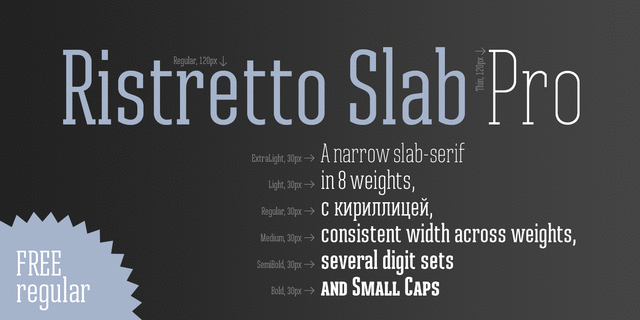
Ristretto Slab Pro – это брусковый компаньон шрифта Ristretto Pro. Это сверхузкий акцидентный шрифт с асимметричными брусковыми засечками, доступный в 8 насыщенностях. Гарнитура поддерживает множество языков, 6 наборов цифр и капитель.
Шрифт Ristretto Slab Pro разработал и выпустил Андрей Константинов в студии Mint Type в 2013 году.
Ассоциации c начертанием Ristretto Slab Pro ThinКачества и характер:
тонкий, стройный, худой, ровный, статичный, высокий, городской, узкий, техничный, качественный, точный, четкий, хрупкий, прозрачный, проволочный